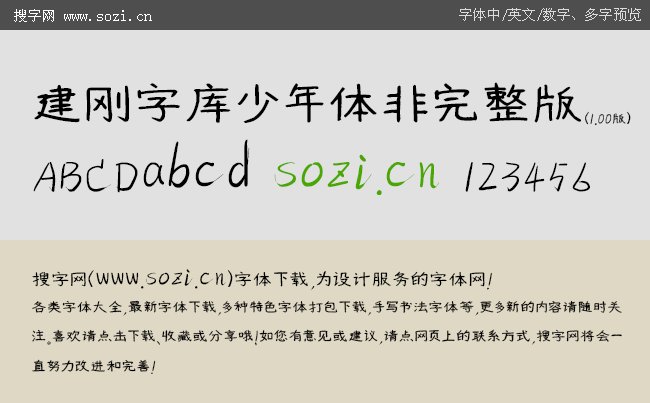
建剛字庫少年體非完整版
搜字網(wǎng)提供一款建剛字庫少年體非完整版中文藝術(shù)字體下載,建剛彤彤體是一款帶有手寫風(fēng)格的中文藝術(shù)字體,字形非常有卡通感,線條細(xì)膩,并且整體效果非常不錯(cuò),可以應(yīng)用于廣告設(shè)計(jì)、名片設(shè)計(jì)、包裝印刷、產(chǎn)品設(shè)計(jì)等方面,有喜歡的朋友可免費(fèi)下載收藏。